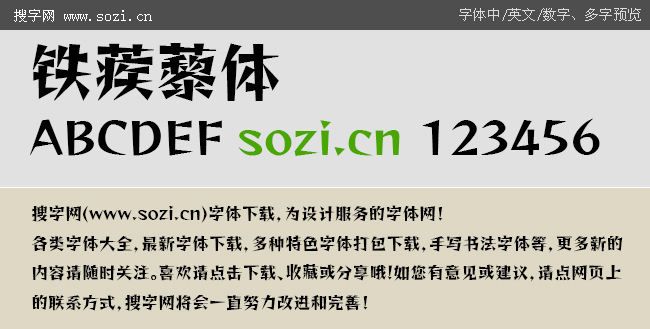
鐵蒺藜體
搜字網(wǎng)給大家提供一款鐵蒺藜體中文字體下載,鐵蒺藜體是一款基于 Fontworks 出品的日文字體レゲエ One 擴(kuò)充、調(diào)整字形,字形凌厲,筆畫末端尖銳突出,具有很好的視覺感。適用于海報(bào)設(shè)計(jì)、網(wǎng)頁設(shè)計(jì)、包裝設(shè)計(jì)等應(yīng)用。